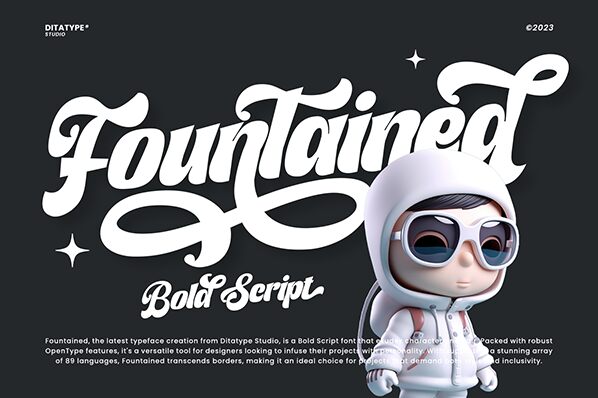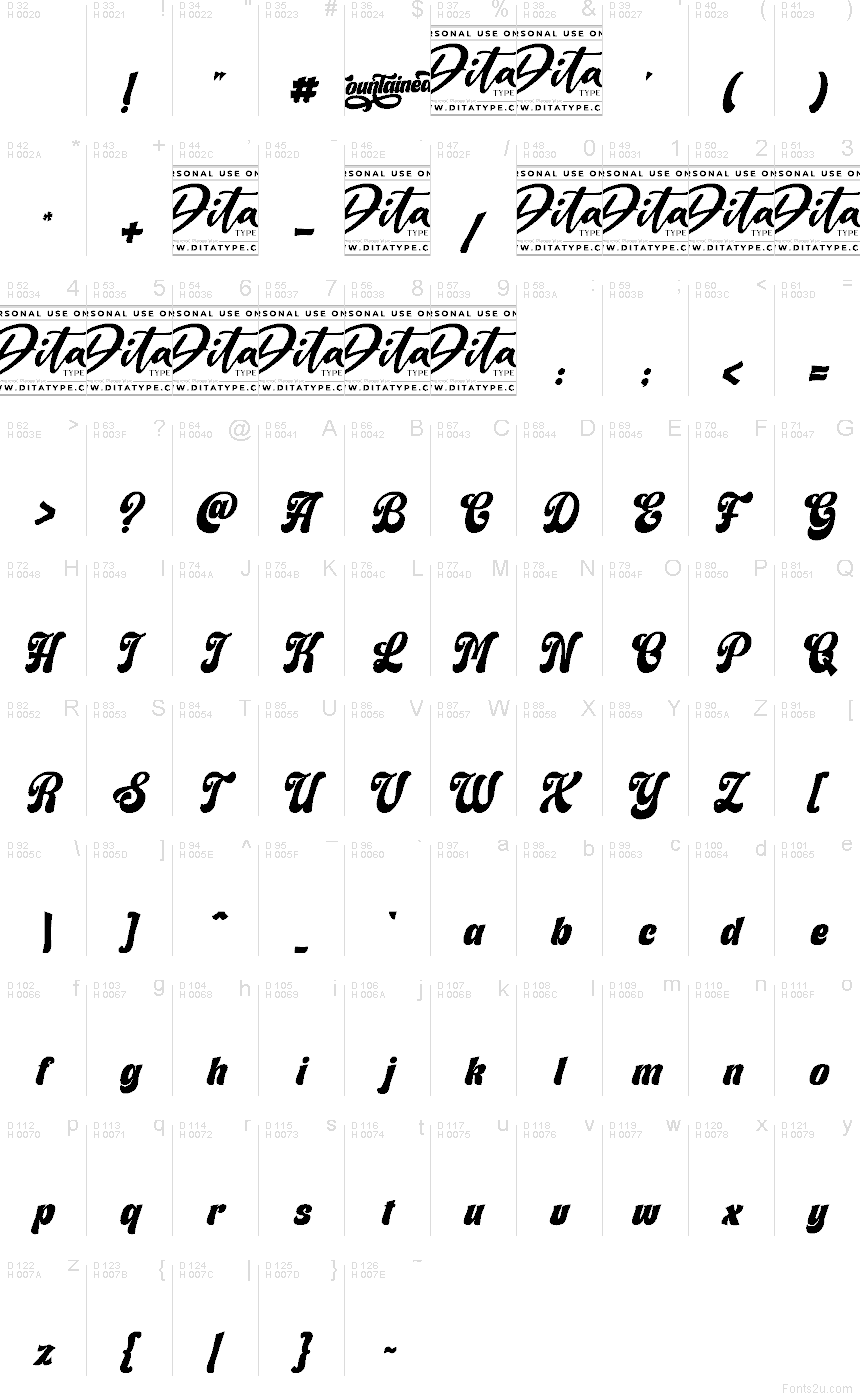
Fountained od Ditatype je bezplatné štětcové písmo s plynulými kurzívními tahy a výrazným skriptovým stylem, který působí dojmem ruční malby spíše než kresby tuhým perem. Písmena se propojují v uvolněném, živém rytmu a zaoblené křivky spolu s ostrými akcenty dodávají písmu silnou rukopisnou přítomnost.
Fountained je bezplatný font, který skvěle funguje v logotypech, na obalech produktů, v nadpisech plakátů, grafikách pro sociální sítě či návrzích krátkých citátů, kde štětcový styl dodává textu osobitost. Hodí se také na pozvánky, branding kaváren nebo obaly alb, zejména pokud hledáte výrazné písmo, které unese nadpis, aniž by působilo příliš formálně.